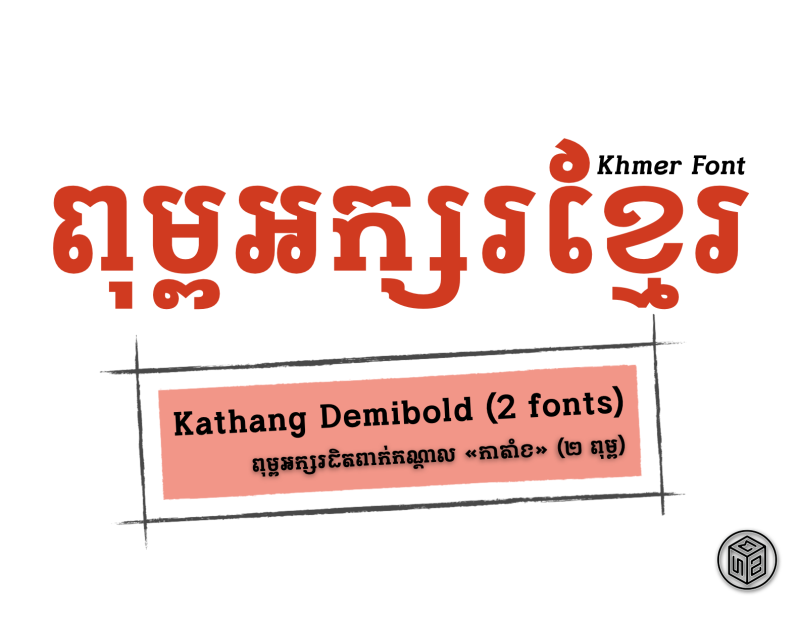
Kathang [Minipack] Demibold (2 fonts)
Single download file of the traditional style slab serif Khmer font - Kathang Demibold
Kathang Demibold​ + Demibold Italic (កាតាំង ដិតពាក់កណ្ដាល + ទ្រេតដិតពាក់កណ្ដាល) ពុម្ពអក្សរខ្មែរ រចនាតាមក្បួនអក្សរខមដែលមានសក់ជាជ្រុង។ ប្រើពុម្ពអក្សរនេះសម្រាប់ការបង្កើត ក្រហ្វិក ការផ្សាយពាណិជ្ជកម្ម និមិត្តសញ្ញា និង ស្លាកយីហោដ៏ស្រស់ស្អាត ដែលសមស្របជាអក្សរធំបង្ហាញ ឬក៏អក្សរក្នុងអត្ថបទ។
Kathang Demibold and Demibold Italic, the Kham-script slab serif Khmer typeface. Use this font to create beautiful graphics, advertisements, logos, and banners that is ideal for Display or Text.